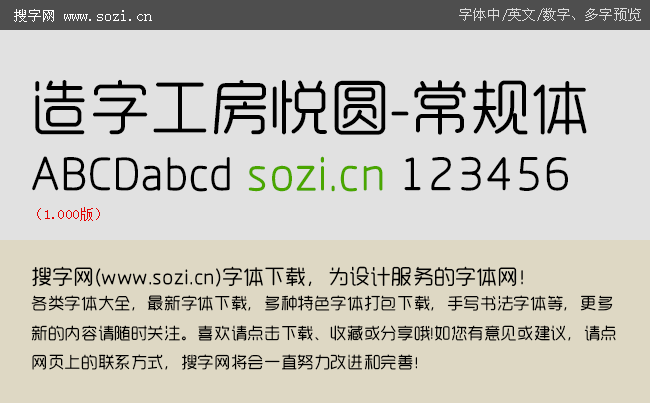
造字工房悅圓常規(guī)體
搜字網(wǎng)為您提供造字工房悅圓常規(guī)字體下載,造字工房悅圓常規(guī)字體為圓體字形,結(jié)構(gòu)秉承悅黑系列,筆畫風(fēng)格簡潔,柔美優(yōu)雅。具有較大范圍的應(yīng)用空間,適用于高端時尚品牌產(chǎn)品的形象設(shè)計與推廣,畫冊及廣告宣傳的正文排版。